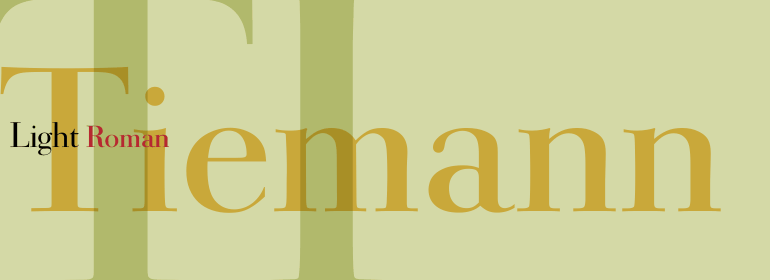
Tiemann™
Tiemann字体由Walter Tiemann于1923年设计,由Klingspor字体铸造厂推出。
它是20世纪上半叶创作的现代书籍字体中的一款,但与大多数现代字体的形式不同。
它显示出相同强烈的笔划对比度和扁平的衬线,但它的比例与新文艺复兴字体的比例更为相似。
Tiemann字体优雅、清晰易读,适用于书籍和较长的文本,但由于其经典而不寻常的外观,也可用于标题、报纸以及杂志。
Tiemann font was designed by Walter Tiemann in 1923 and appeared with the Klingspor font foundry.
It is one of the modern book fonts created in the first half of the 20th century, but differed from most in its Modern Face forms.
It displays the same strong stroke contrast and flat serifs but its proportions have more in common with those of neorenaissance fonts.
Tiemann is an elegant, legible font suitable for books and longer texts, but also found in headlines, newspapers and magazines due to its classic yet unusual appearance.